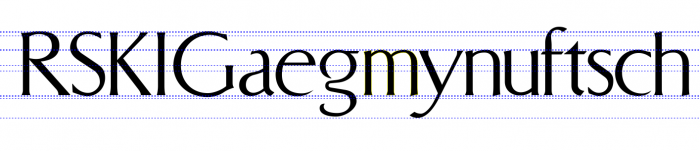
Eine Frage an die Schriftgestalter
Jetzt hätte ich einmal eine Frage an die Schriftgestalter hier im Forum.
Ich habe nämlich wieder mal folgendes Problem: Ich weiß, am Anfang eines Schriftentwurfes stehen meistens Skizzen. Am Ende steht meist das Herumschieben von Bézier-Anfasserpunkten am Computer. Dazwischen muss der auf dem Papier erstellte Entwurf in den Computer; über Scanner oder andere Digitalisierungsinstrumente.
Aber was kommt kurz vor der Digitalisierung und Weiterbearbeitung? Sprich: Wie ausgereift sollte der Entwurf für effizientes Arbeiten schon auf dem Papier sein? Ich habe gehört, in den Zeiten vor Vektor-Fonts (und vielleicht oft auch heute noch) seien die Reinzeichnungen oft mit Tusche gezeichnet und dann mittels Rasierklinge etc. nachgebessert worden, bis sie zufriedenstellend waren.
Ich habe das auch schon ausprobiert, musste dann aber feststellen, dass der Entwurf im PC plötzlich ganz furchtbar aussah und ich wieder viel Zeit mit den Bézierkurven verbringen musste. Toll, dachte ich mir, dann hätte eine Bleistiftzeichnung mit 4 cm x-Höhe auch gereicht! Andererseits musste ich auch feststellen, dass die Entwürfe zu mechanisch, langweilig, kraftlos und kompromissbehaftet werden, wenn sie zu einem Großteil am PC entstehen.
Dazu kommt noch das merkwürdige Paradoxon, das man vielleicht Unschärferelation der Skizze nennen könnte: Nämlich, dass (zumindest bei mir) kleine Skizzen tendenziell eher ausdrucksstärker sind als größere, dafür aber natürlich ungenauer. Und umgekehrt. Manchmal habe ich auch so eine Skizze vor mir, von der ich denke, sie wäre perfekt, bis auf dieses kleine Detail. So, was tun? Den Buchstaben durchpausen? Möglichst genau abzeichnen? Dann hakt es meistens wieder an anderer Stelle.
Kurz: Wie stellt ihr das an, wie wird aus einem Entwurf eine Reinzeichnung? Oder anders gefragt: Wie wichtig ist eine Reinzeichnung überhaupt? Ich bin mir ziemlich sicher, dass das jeder ein wenig anders handhabt, bestimmt sogar von Entwurf zu Entwurf unterschiedlich. Ich wollte mir daher nur mal ein paar Meinungen dazu anhören, damit ich mir ein Bild davon machen kann, wie es ablaufen kann.
Ich gehe bei Fonts, die (wie jetzt der Linz-Straßenschilder-Font, bei dem die Skizze ein Foto ist) oder bei eigenen Ideen so vor:
1. Ist es die eigene Idee, dann erst mal die kleine flüchtige Blei-Scribble-Skizze. Einscannen, und damit vergrößert ausdrucken (blass)
2. diese Verrgrößerte Skizze wird dann gesäubert, also tatsächlich sorgfältiger nachgezeichnet, allerdings von Hand und Bleitift, das reicht. Man kann so eierige Ecken radieren, und sauberer zeichnen. Auf Papier, weil ich das nach belieben zur Hand drehen kann,
3. das Ergebnis erneut scannen, aber nicht per Autotrace digitalisierten, da hat mein keinerlei Kontrolle, wo das System die Knoten setut, und das herumgezuppel an Vektoren ist nicht mein Ding. Also nutze ich CorelDraw, weil ich hier nicht an Ankern ziehen muss, sondern direkt an der Kurve ziehen kann. Da importiere ich den Scan, und packe ihn in eine Ebene, die ich vor Bearbeitung schütze. Zeichnen tue ich auf einer 2. Ebene darüber
4. Jetzt zeichne ich mit dem Freihand-Werkzeug einen Verlauf von geraden Lionien von Extrrempunkt der Kuntur zu Extrempunkt, also bei Bögen jeweild den (geschätzten) Punkt, der am höchsten oder tiefsten oder am weitesten links oder rechts ist, oder woi die Kurve einen spitzen Winkel hat, oder ein Bogen in eine Gerade über geht. Ich vermeide es nach Möglichkeit mehr Punkte zu setzen.
5. Anschließend wandele ich die Abschnitte, die keine Gerade sind in Kurven, und ziehe sie an der Kurve an meine gezeichnete oder fotografierte Kontur heran, fasse dann erst die Kontrollpunkte an, und korrigiere sie so, dass diese bei Knoten an Extrempunkten genau in der Waagerechten oder Senkrechten zum Kurven-Knoten liegen.
6. Dabei teile vich meine Buchstaben möglichst in Teilabschnitte ein, deren Form auch bei anderen. Buchstaben wiederkehrend genutzt werden können, wie hier im Beispiel der Stamm des R mit seiner Grund-Serife.
7. Habe ich so alle Elemente beisammen, um daraus alle Buchstaben zu kombinieren, nutze ich die Verschmelzungs-Werkzeige in meinem Vektor-Grafikprogramm, und habe dann hier noch alle Buchstaben nebeneinander, und kan sie so sogar schon miteinander wirken lassen.
8. Die so gezeichneten Glyphen exportiere vich als Block (also z.B. alle Gemeinen) in eine EPS-Datei und importiere diese dann in ein Glyphenfenster in Fontlab, beispielsweise, habe iuch die gemeinen importiert, in das a, in dem dann allerdings das ganze Alfabet drin ist. Diese Glyphe kopierte ich dann einfach, so wie sie ist in alle anderen Gemeinen im Font-Fenster. Jetzt Öffne ich eiune Glyphe nach der anderen, markiere mit Strg+A alles, und demarkiere nur den Buchstaben, der bleiben soll, kurzer Klick auf Entf, und die vjeweiligev Glyphe ist vereinzelt, diesen Schritt wiederhole ich durch das komplette Alfabet. das geht so schneller als jeden Buchstaben einzeln zu importieren. Als letzter Schritt werden diesen Buchstaben über Tools - Action - Metrics - Set Sidebearings  (ich verwende die englische Version) den Buchstaben zunächst eine einheitliche Vor- und Nachbreite verpasst, bevor ich diese je nach spezieller Buchstabenform von Hand anpasse.
Ja, das meinte ich eben. Wenn man selber seine Schrift am Computer digitalisiert, kann man da natürlich noch beliebig ausgiebig die digitale Rasierklinge ansetzen. Wie ich aber schon sagte, habe ich dann die Erfahrung gemacht, dass man zu viel an der Schrift rumdoktert, die dann am Ende zwar harmonischer aussieht als die Skizzen, dafür aber auch kraftloser.